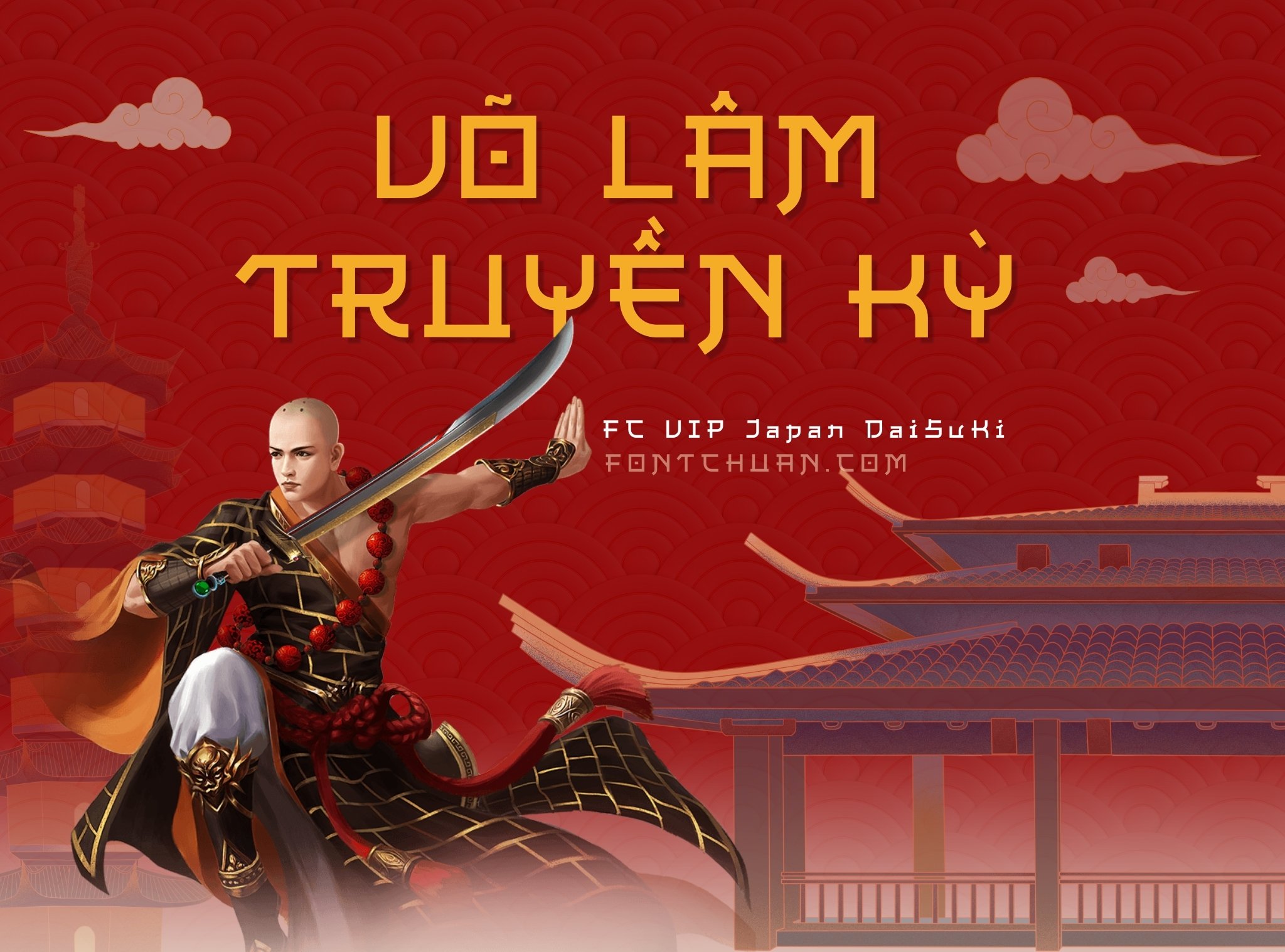
Japan Daisuki là một Font Sans-serif đậm, được thiết kế bởi Muhamad Yusron Billah và phát hành bởi Sronstudio. Font này lấy cảm hứng từ phong cách truyền thống Nhật Bản, kết hợp với thiết kế hình học hiện đại, tạo nên sự mạnh mẽ và tinh tế. Japan Daisuki hỗ trợ bao gồm cả tiếng Việt nhưng chưa được tối ưu, ngoài ra font có đa ngôn ngữ, giúp nhà thiết kế tiếp cận đối tượng rộng rãi.
Về thiết kế, Japan Daisuki sở hữu các đường nét rõ ràng, cấu trúc chữ cân đối và phong cách hiện đại, phù hợp cho nhiều mục đích sử dụng như thiết kế logo, tiêu đề, poster sự kiện, ấn phẩm game thuần việt, game kiếm hiệp, poster âm nhạc hay poster phim cổ trang, và các ấn phẩm quảng cáo khác.